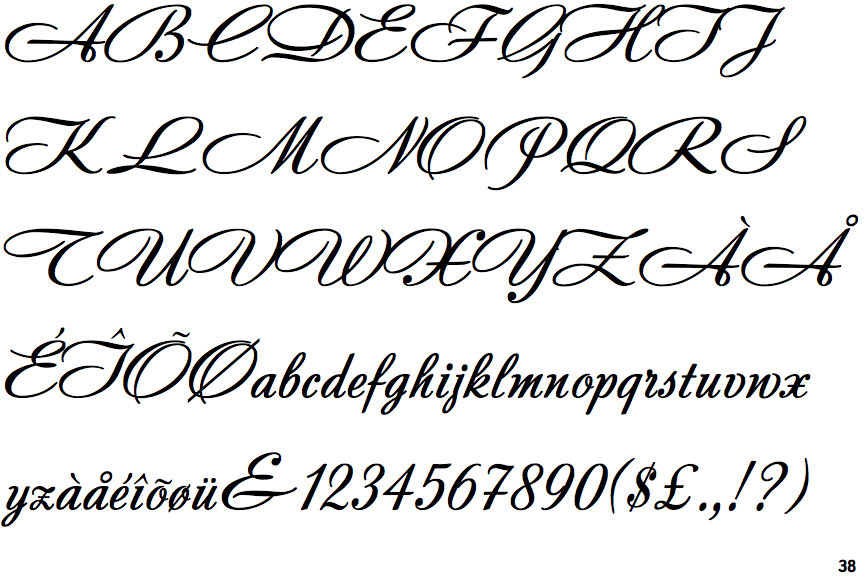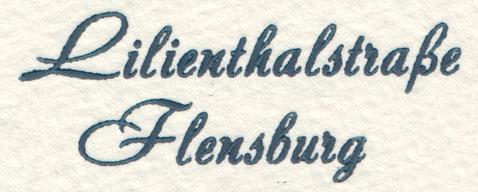
Noch eine Bleisatzschrift, die ich nicht finde ...
Ziemlich sicher auch aus den 50er Jahren - wie alles Schriften, die in diesem Schrank sind.
Aber welche?
(WhatTheFont etc. habe ich schon durch!)
die Suche nach der Schrift ergab erst mal nix aus dem Digitalium, daher noch dieser Nachschlag:
Typeface:	Andantino
Designers:	Karl Klauß and Jason Walcott
Year:		1953, 2003
Publisher:	Jukebox
A revival of Adagio, designed by Karl Klauß in 1953.